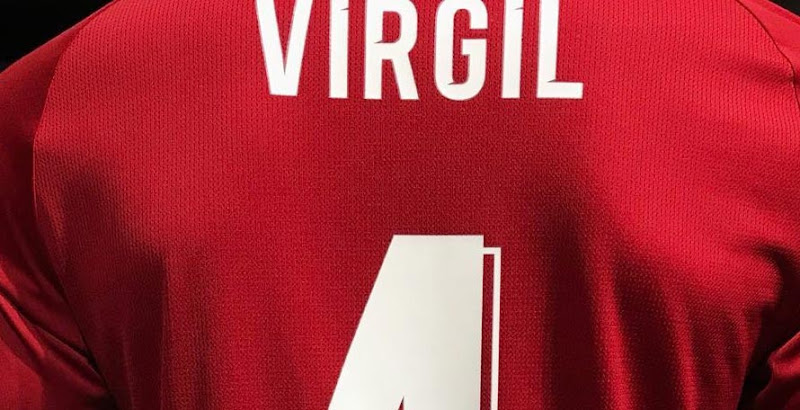
Liverpool wird mit Nike in der Saison 2020/21 die gleiche Pokal / Champions League Schriftart verwenden
Liverpool hat in diesem Monat endlich das neue Heimtrikot herausgebracht, ihr erstes von Nike. Damit erhalten wir auch einen Blick auf die Pokal-Schrift, die Liverpool in der Saison 2020/2021 verwenden wird. Es ist aber nichts Neues.
Liverpool 2020-2021 Trikot-Schriftart - Unverändert - Von Club entworfen
Die maßgeschneiderte Liverpool-Schriftart wurde vom Club vor der Saison 2018/2019 erstellt und präsentiert.
Die benutzerdefinierte Liverpool Trikot-Schriftart "wurde so gestaltet, kultige Charakteristika des Anfield Stadium und des umliegenden Bereichs zu verkörpern".
Die Liverpool Trikot-Schriftart wird in der Saison 2020/2021 sowohl bei internationalen Wettbewerben als auch bei Pokalspielen verwendet, während der Verein bei Spielen der Premier League die Premier League Schriftart verwenden wird.